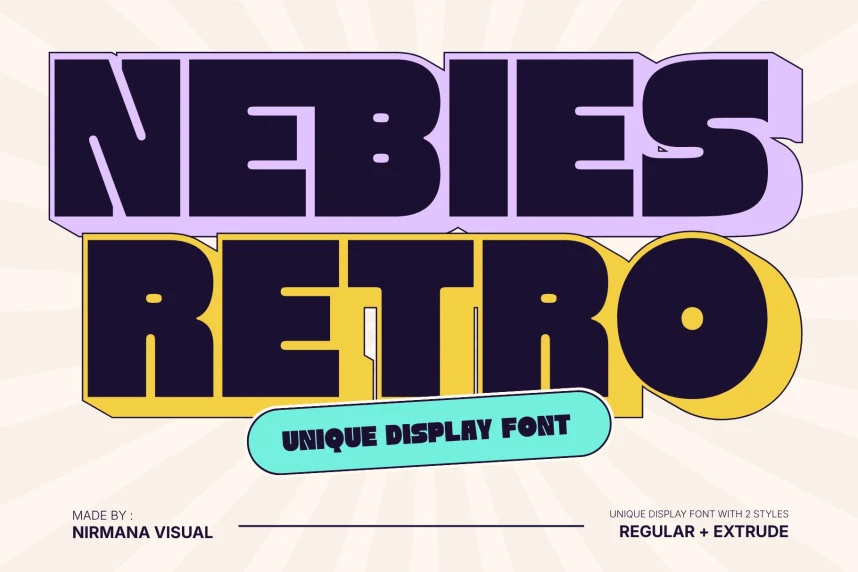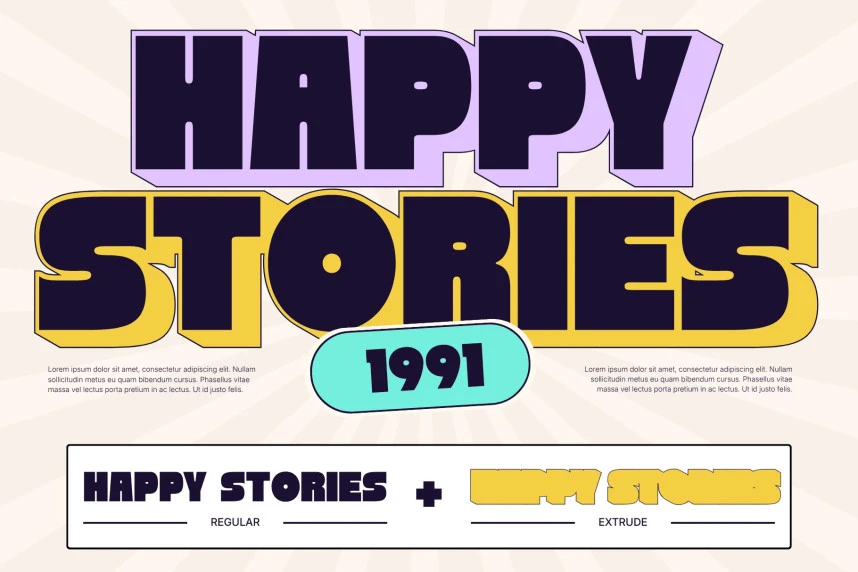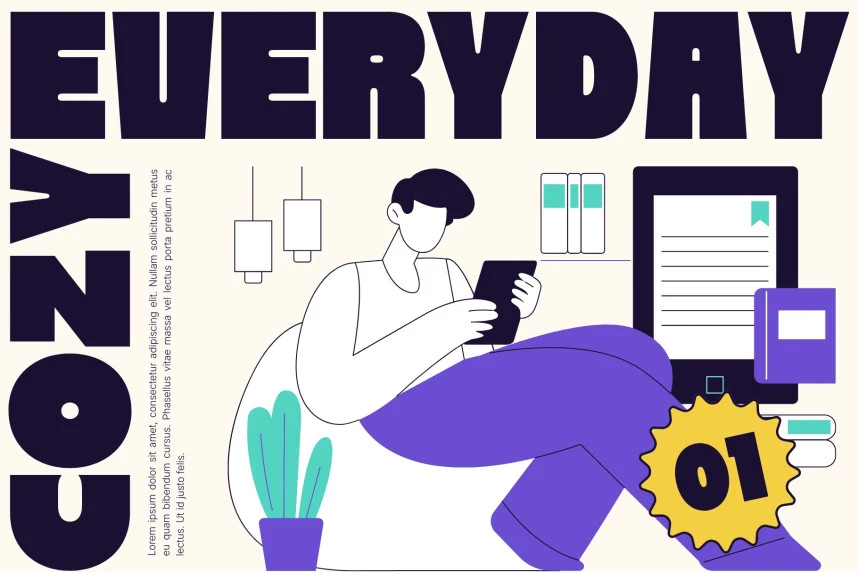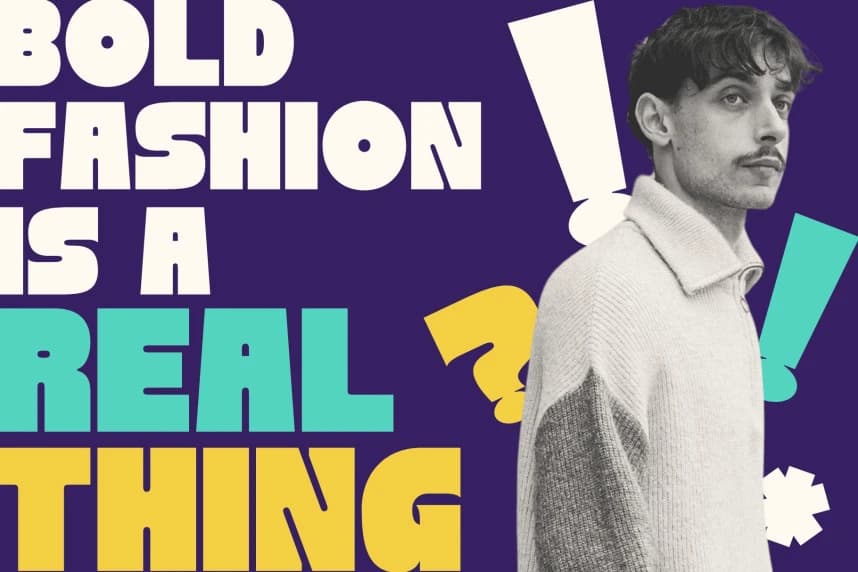
Nebies Retro Font, modern markalaşmaya nostalji tadı katmak için tasarlanmış cesur ve eğlenceli bir gıda fontudur. Kalın hatlı harfleri ve akıcı eğrileriyle, eğlenceli ve iştah açıcı bir vintage hava yakalar.
Nebies Retro Font cesur, oyuncu bir yiyecek fontudur ve modern markalaşmaya nostalji tadı katmak için tasarlanmıştır. Kalın hatları ve yumuşak eğrileriyle eski moda bir hava yakalar; hem eğlenceli hem de iştah açıcı bir his verir.